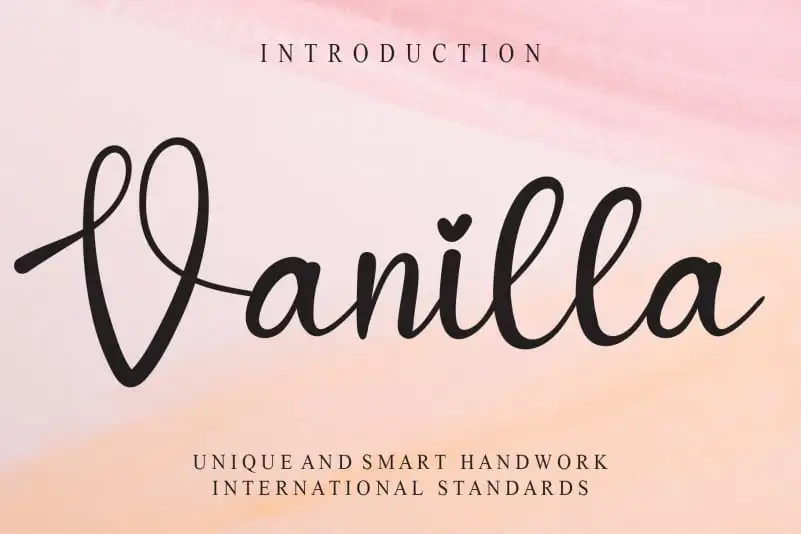
Descubra a Vanílha Script Font, uma nova opção de script para seu projeto. Com seu designer criativamente concebido, você vai experimentar uma experiência única e especializada. Este tipo de letra é perfeito para criar textos elegantes e bem-aventurados em projetos gráficos variados, desde assinaturas sofisticadas até designs para editoriais de moda. Seja seu próximo projeto um evento de inovação digital ou a criação de uma capa memorável para sua newsletter, a Vanílha Script oferece a perfeita mistura de estilo e facilidade na hora da escrita. Engane-se em experiências imersivas com esta fonte, criada especialmente para você. Experimente já e explore o mundo sem limites da design gráfico digital.